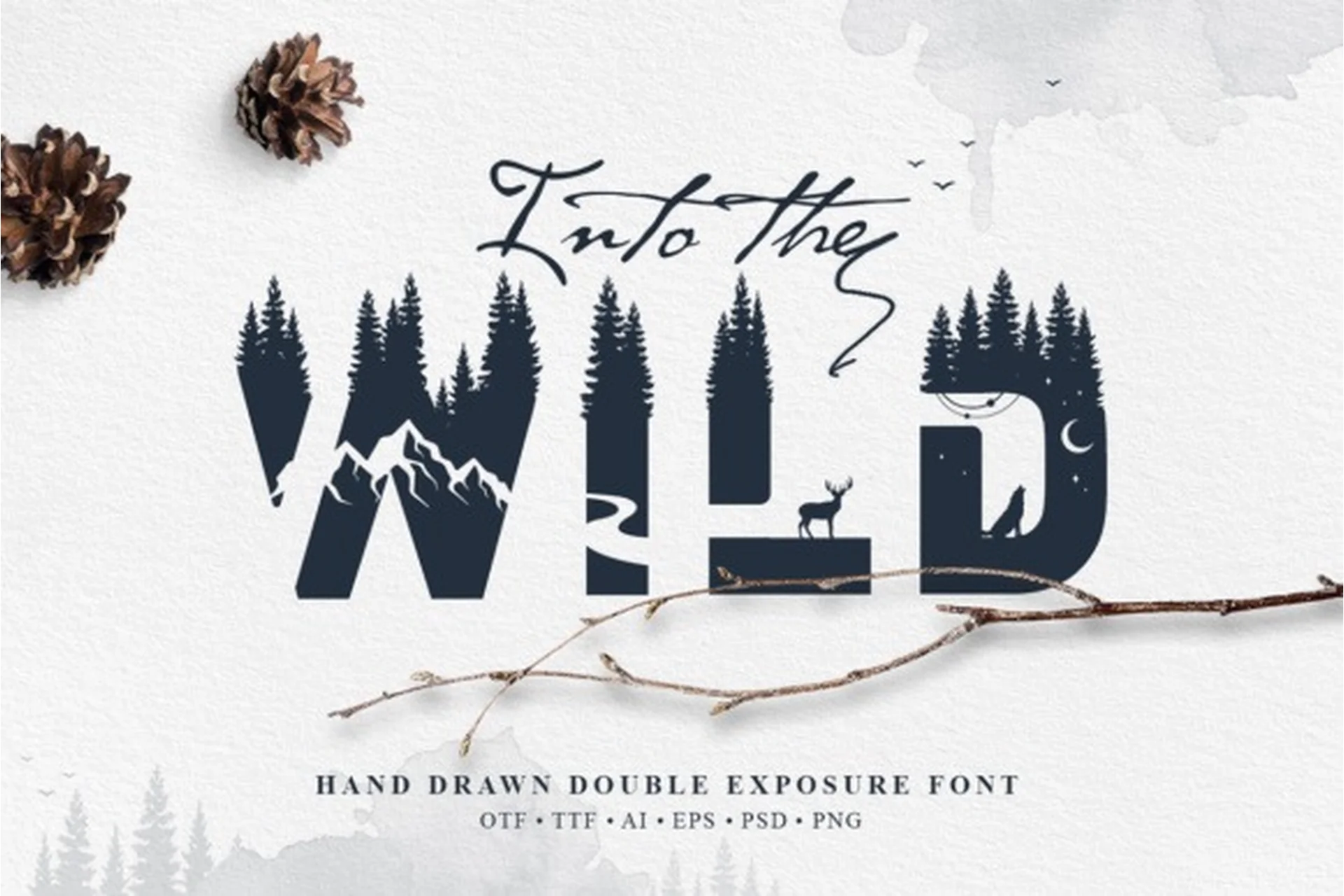
Into The Wild- это современный шрифт с эффектом двойного воздействия, который будет прекрасно смотреться в ваших дизайнерских проектах.
Каждая буква была сделана вручную и имеет забавные дополнительные элементы, такие как деревья, животные, автомобили, водопады и многое другое! Также в качестве бонуса прилагаются забавные предметы!